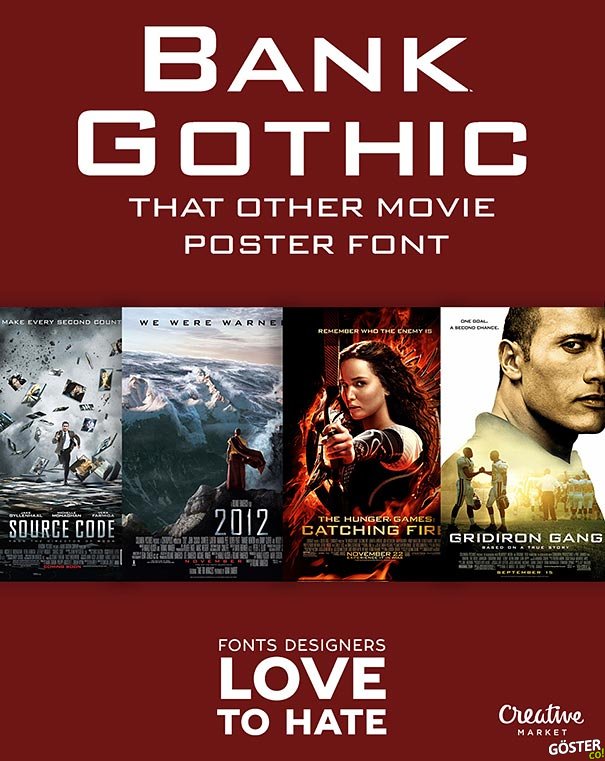
İnsanların Nefret Etmekten Keyif Aldığı 11 Yazı Tipi
Bank Gothic: Bir diğer film afişi...
İnsanların Nefret Etmekten Keyif Aldığı 11 Yazı Tipi
Bank Gothic: Bir diğer film afişi...
Bank Gothic: Bir diğer film afişi fontu.